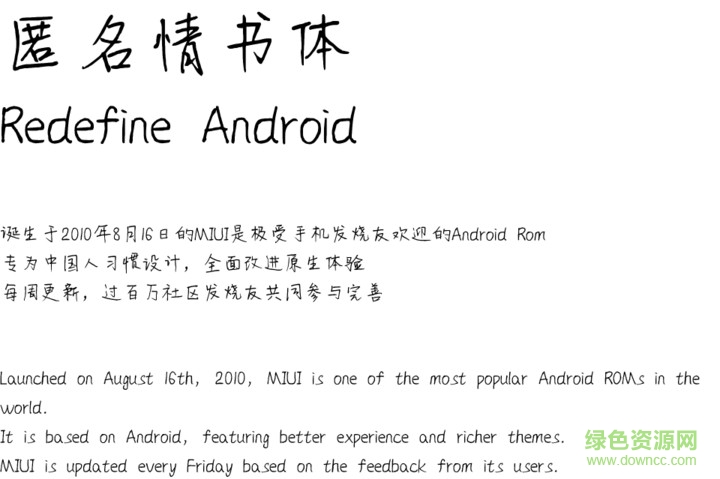
匿名情書體是兄弟字庫推出一款手寫情書字體,帶給你怦然心動的獨特體驗,字體干凈無任何修飾,表達(dá)了最原始的純粹和質(zhì)樸的感情,喜歡的朋友就來綠色資源網(wǎng)一起體驗吧!
收到某人的匿名情書,第一次體會到“小鹿亂撞”的感覺!你可以將其用于書信設(shè)計、海報設(shè)計、雜志設(shè)計等創(chuàng)意設(shè)計方面。